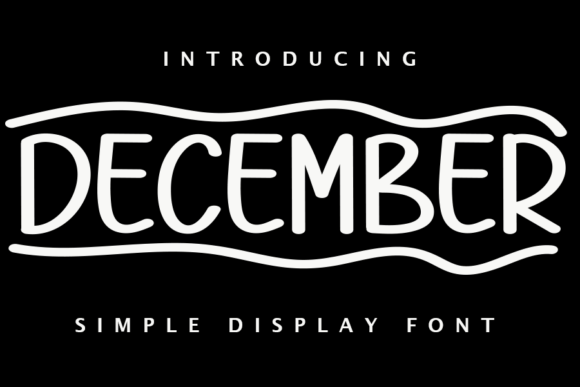
December Font
December Font – لمسة أنيقة لمشاريعك الإبداعية
أضف لمسة من الأناقة والدفء إلى تصاميمك مع خط December، الخط المثالي للمصممين وصناع المحتوى الذين يبحثون عن طابع عصري وجذاب. يتميز هذا الخط بأسلوبه الأنيق والمنحني، مما يجعله مثاليًا لمجموعة متنوعة من الاستخدامات، مثل:
✅ تصاميم العلامات التجارية والشعارات
✅ بطاقات المعايدة والدعوات
✅ منشورات وسائل التواصل الاجتماعي
✅ أغلفة الكتب والمجلات
✅ تصميمات الطباعة والمنتجات الرقمية
✨ اجعل إبداعاتك تنبض بالحياة مع December Font! ✨